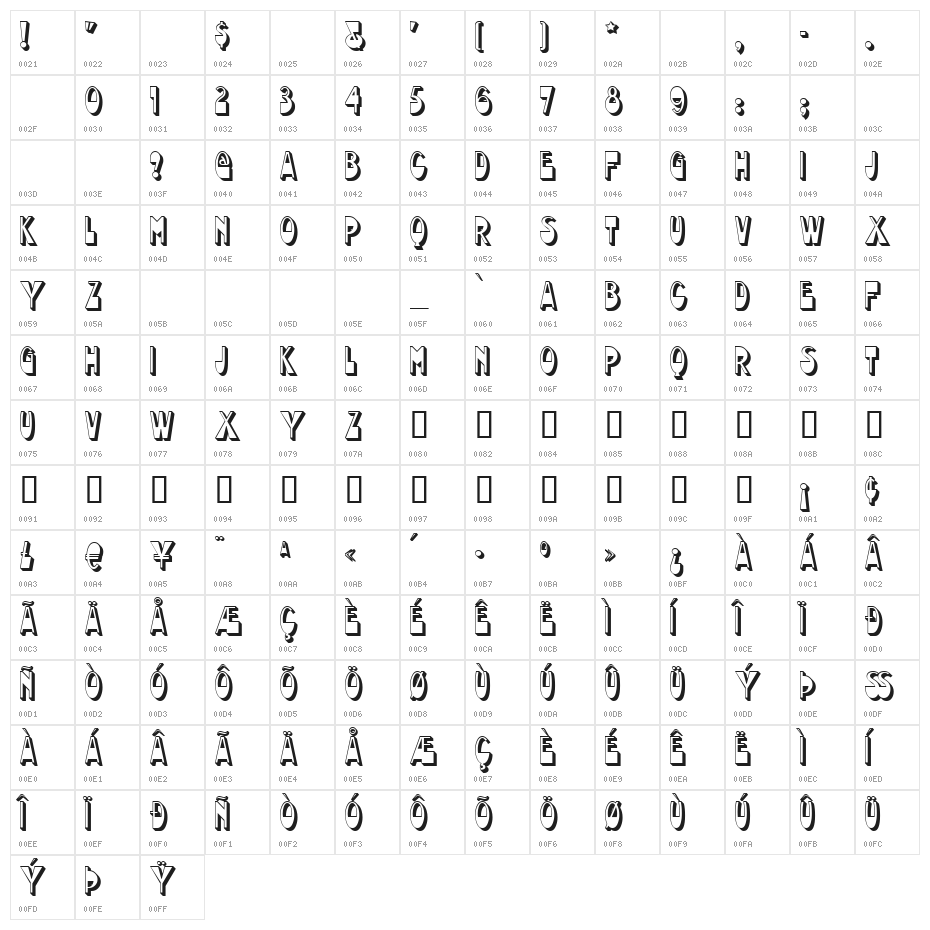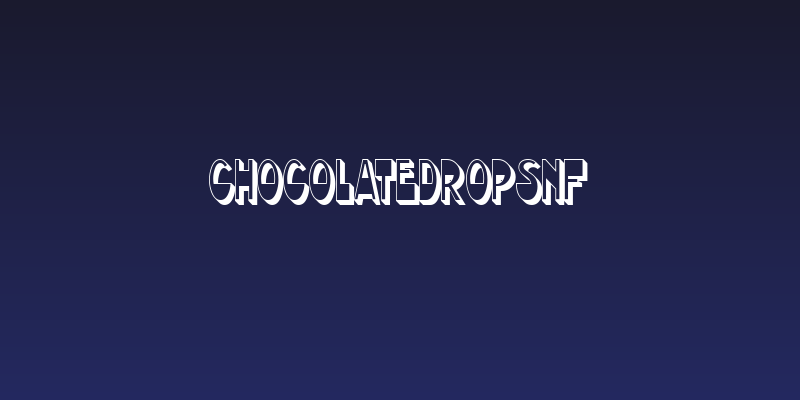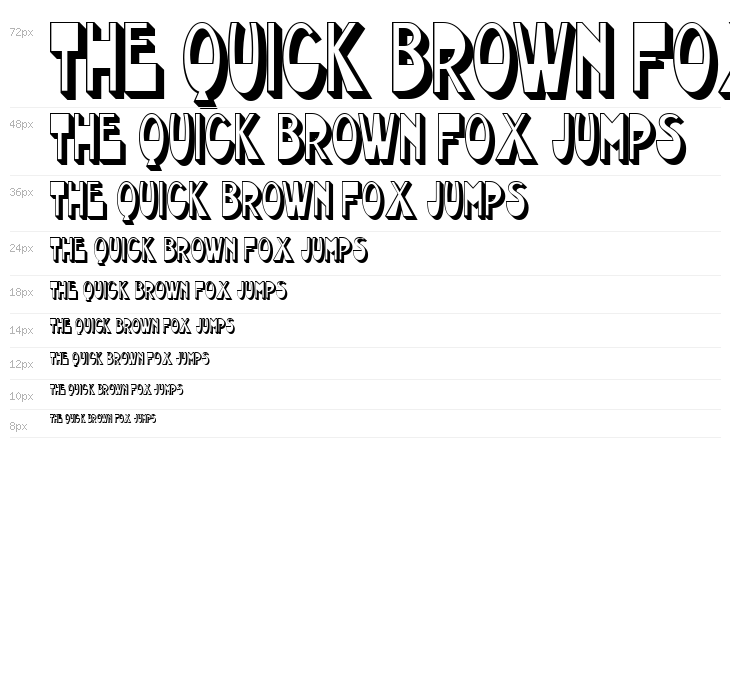
ChocolateDropsNF Font
✎ 3D
| Stile generale | Playful, Fun, Dynamic |
| Progetti proposti | Children's books, posters, playful branding, headlines, and titles. |